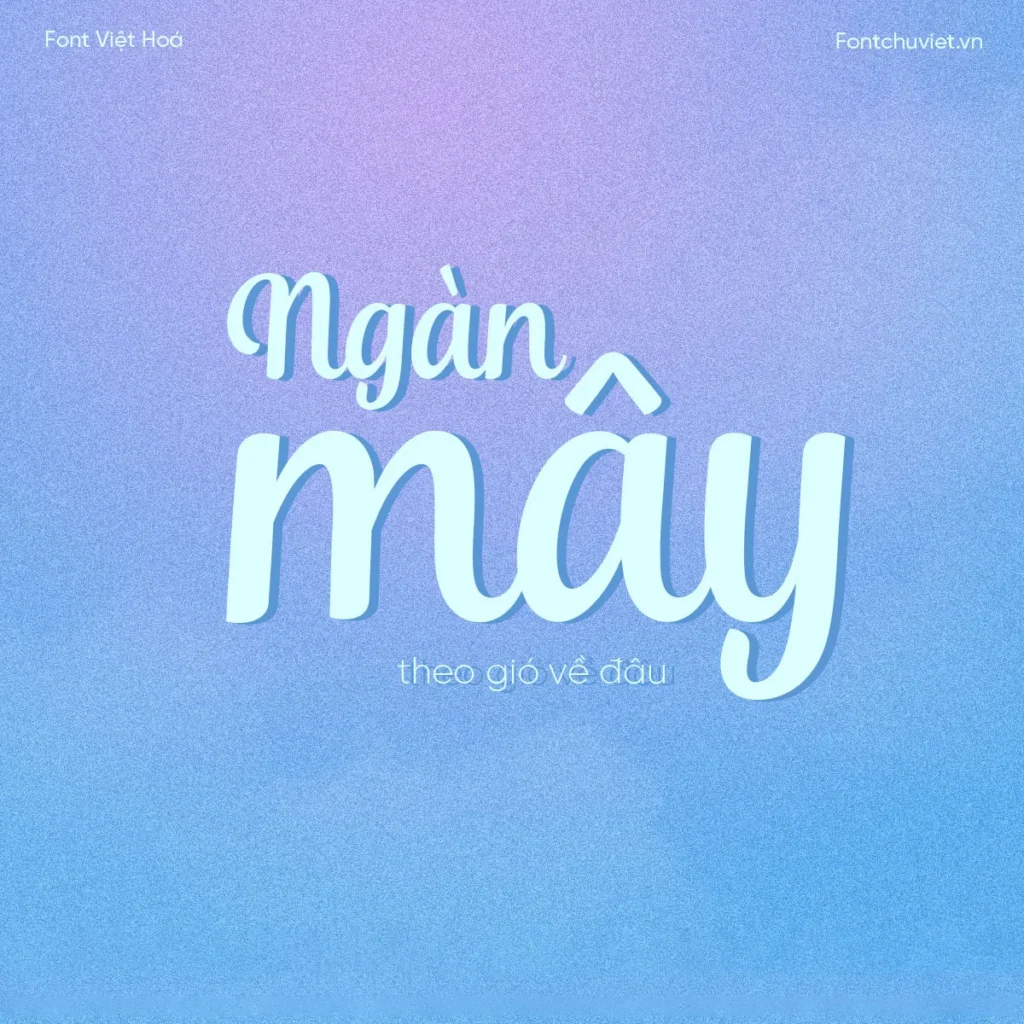
Font VL Andalusia – Font Việt hoá là font viết tay đậm. Dùng cho tiêu đề thì phù hợp, dùng cho in ấn trên ly, áo thun cũng rất hợp lý. Có thể nhìn thấy từ xa khi nhìn vào các thiết kế.
Font VL Andalusia – Font Việt hoá Là Gì?
Font VL Andalusia – Font Việt hoá là một trong những font viết tay đậm được sử dụng rộng rãi trong thiết kế đồ họa. Với đặc điểm đậm, nét viết tay rõ ràng, font này rất phù hợp cho việc tạo tiêu đề, quảng cáo, in ấn.
Ứng Dụng Của Font VL Andalusia – Font Việt hoá
Trong Thiết Kế Đồ Họa
Font VL Andalusia – Font Việt hoá được sử dụng rộng rãi trong thiết kế đồ họa, đặc biệt là trong việc tạo tiêu đề, quảng cáo, in ấn.
Trong In Ấn
Font này cũng rất phù hợp cho in ấn trên ly, áo thun, và các sản phẩm khác.
Lợi Ích Của Font VL Andalusia – Font Việt hoá
Font VL Andalusia – Font Việt hoá có nhiều lợi ích, bao gồm:
- Dễ đọc
- Dễ nhìn
- Phù hợp cho nhiều ứng dụng
Font VL Andalusia – Font Việt hoá là một lựa chọn hoàn hảo cho tiêu đề, in ấn trên ly, áo thun. Hãy tải xuống và sử dụng font này ngay hôm nay!